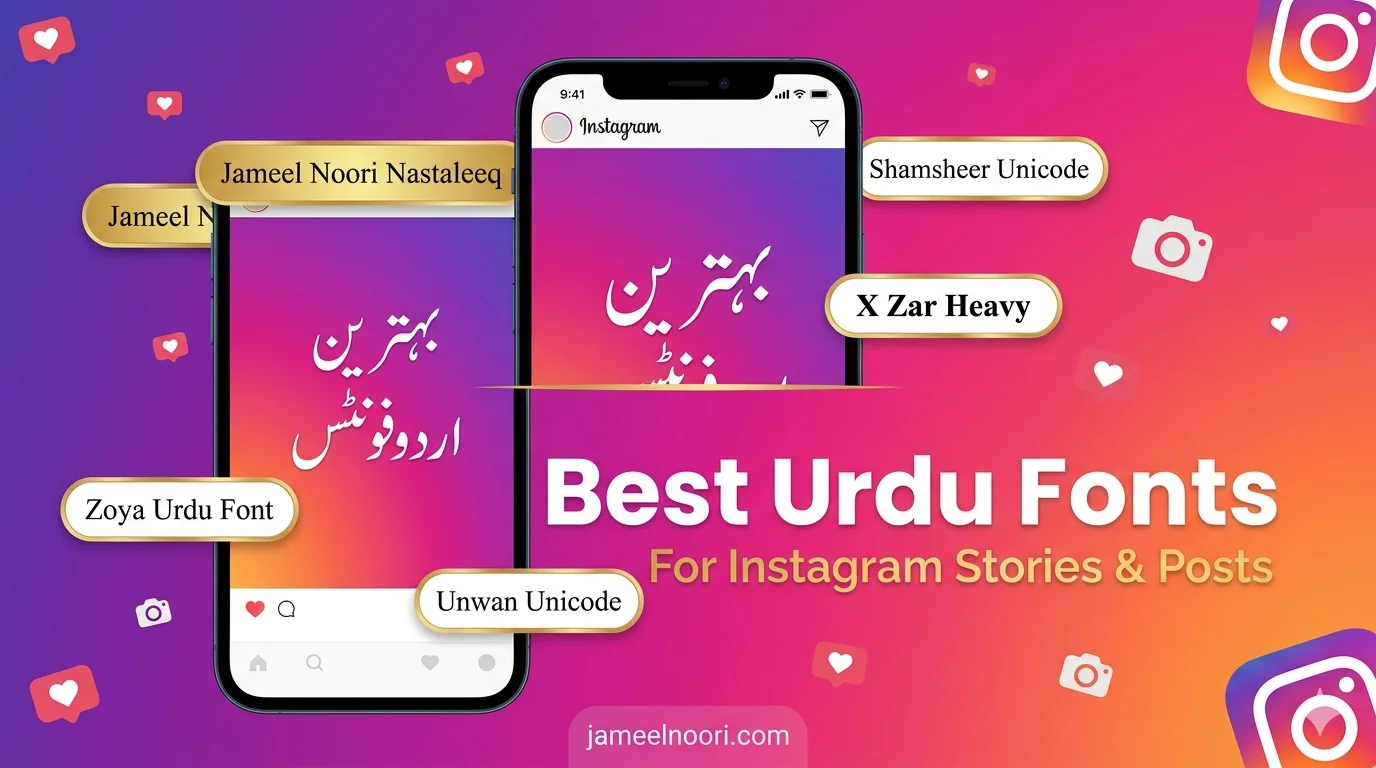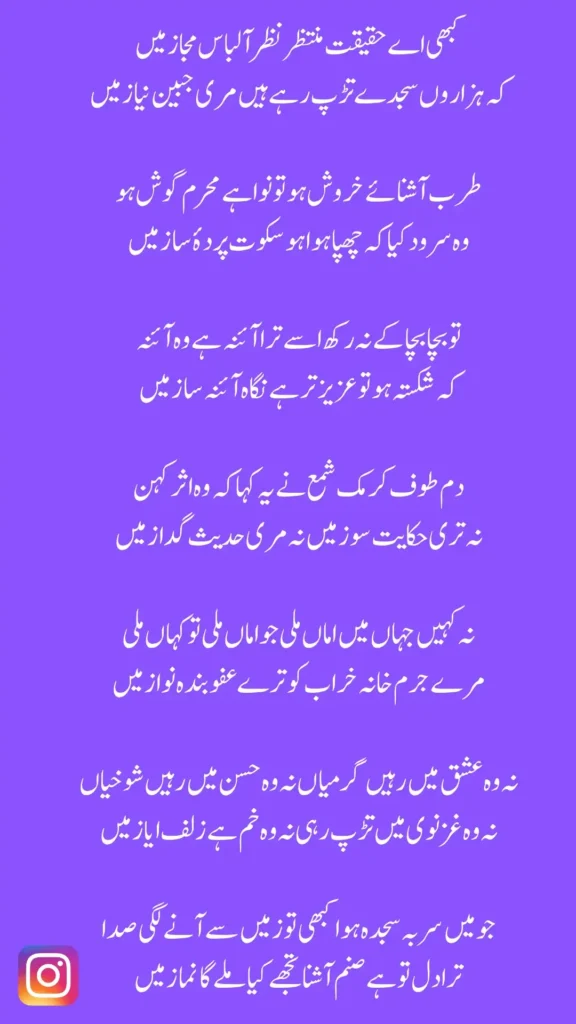
Best Urdu Fonts for Instagram Stories & Posts
Instagram Par Urdu Fonts Ki Zaroorat Kyon Hai?
Instagram par aap ne dekha hoga ke kuch posts par likhai bohot achi lagti hai, aur kuch par text bilkul dull lagta hai. Farq sirf font ka hota hai.
Agar aap Urdu mein Instagram stories ya posts banate hain, toh font ka choice bohot matter karta hai. Ghalat font select karne se log skip kar dete hain. Sahi font se engagement barh jaati hai.
Best Urdu Fonts for Instagram Stories ki list mein aaj hum aap ko kuch aise fonts batayenge jo:
• Mobile screen par clear dikhte hain
• Stylish bhi hain aur readable bhi
• Canva, PicsArt, aur Instagram app mein use ho sakte hain
Free Urdu Fonts mein se yeh fonts Instagram ke liye best hain:
Urdu poetry by Allama Iqbal written in Jameel Noori Nastaleeq font – ستاروں سے آگے جہاں اور بھی ہیں۔ ابھی عشق کے امتحاں اور بھی ہیں۔
ستاروں سے آگے جہاں اور بھی ہیں۔ ابھی عشق کے امتحاں اور بھی ہیں۔
Allama Iqbal ki mashhoor shayari Jameel Noori Nastaleeq font mein. Urdu poetry lovers ke liye best for Instagram stories and posts.
Urdu poetry written in Jameel Noori Nastaleeq font – کہے اے حقیقت نگاہ ظفر اللباس مجاز میں۔ کہ ہزاروں جیسے تڑپ رہے ہیں مری جبیں نیاز میں۔
کہے اے حقیقت نگاہ ظفر اللباس مجاز میں
کہ ہزاروں جیسے تڑپ رہے ہیں مری جبیں نیاز میں
Deep emotional Urdu poetry in beautiful Jameel Noori Nastaleeq calligraphy style. Perfect for Instagram stories, Urdu poetry lovers, and shayari posts.
Instagram Ke Liye Font Mein Kya Dekhna Chahiye?
Pehle yeh samajh lete hain ke Instagram story ya post ke liye font mein kya qualities honi chahiye:
QualityWhy It Matters
BoldnessMobile screen par light fonts dikhte nahi
Clear spacingLetters aapas mein milne se parhna mushkil ho jata hai
Modern lookOld style fonts Instagram vibe match nahi karte
Quick readabilityLog 2-3 seconds mein text parh sake
CompatibilityCanva, PicsArt, Instagram app mein kaam kare
Agar font yeh qualities rakhta hai, toh wo Instagram ke liye perfect hai.
Jameel Noori Nastaleeq traditional hai lekin Instagram ke liye bhi kaam karta hai:
Zoya Urdu Font stylish aur elegant hai:
Zohar Unicode Font modern look deta hai:
Top 10 Best Urdu Fonts for Instagram Stories
Yeh meri personally tested list hai. Maine in fonts ko Instagram stories mein use kiya hai aur result acha aaya hai.
1. Jameel Noori Nastaleeq
Classic font hai. Poetry aur Islamic posts ke liye best. Thoda heavy hai lekin headings ke liye zabardast lagta hai.
Best for: Poetry, Quranic verses, Naat posts
Style: Traditional calligraphy
2. Zoya Urdu Font
Bohot stylish hai aur mobile screen par clear dikhta hai. Modern look chahiye toh yeh lo.
Best for: Quotes, fashion posts, beauty content
Style: Modern, elegant
3. Zohar Unicode
Clean hai aur minimal look deta hai. Informative posts ke liye best.
Best for: Educational posts, tips, facts
Style: Clean, minimal
Zohar Unicode Font – modern and readable Unicode Urdu font for digital and print
4. Shamsheer Unicode
Bold hai aur screen par bohot clear dikhta hai. Thumbnails aur headings ke liye best.
Best for: Headlines, announcements, call to action
Style: Bold, clear
Shamsheer Unicode Urdu Font sample image in Nastaliq script – elegant and classic Urdu typography preview
Elegant Shamsheer Unicode Urdu Font for stylish writing and web design.
5. Unwan Unicode
Elegant calligraphy style hai. Wedding posts, event announcements ke liye perfect.
Best for: Events, invitations, special announcements
Style: Calligraphy, elegant
Unwan Unicode Font image – modern and stylish Unicode Urdu font for digital and print
6. X Zar Heavy
Bohot bold hai. Attention grab karna hai toh yeh lo. Thoda unique look deta hai.
Best for: Sale posts, promotions, urgent announcements
Heading ke liye 40-50px, body text ke liye 20-25px.